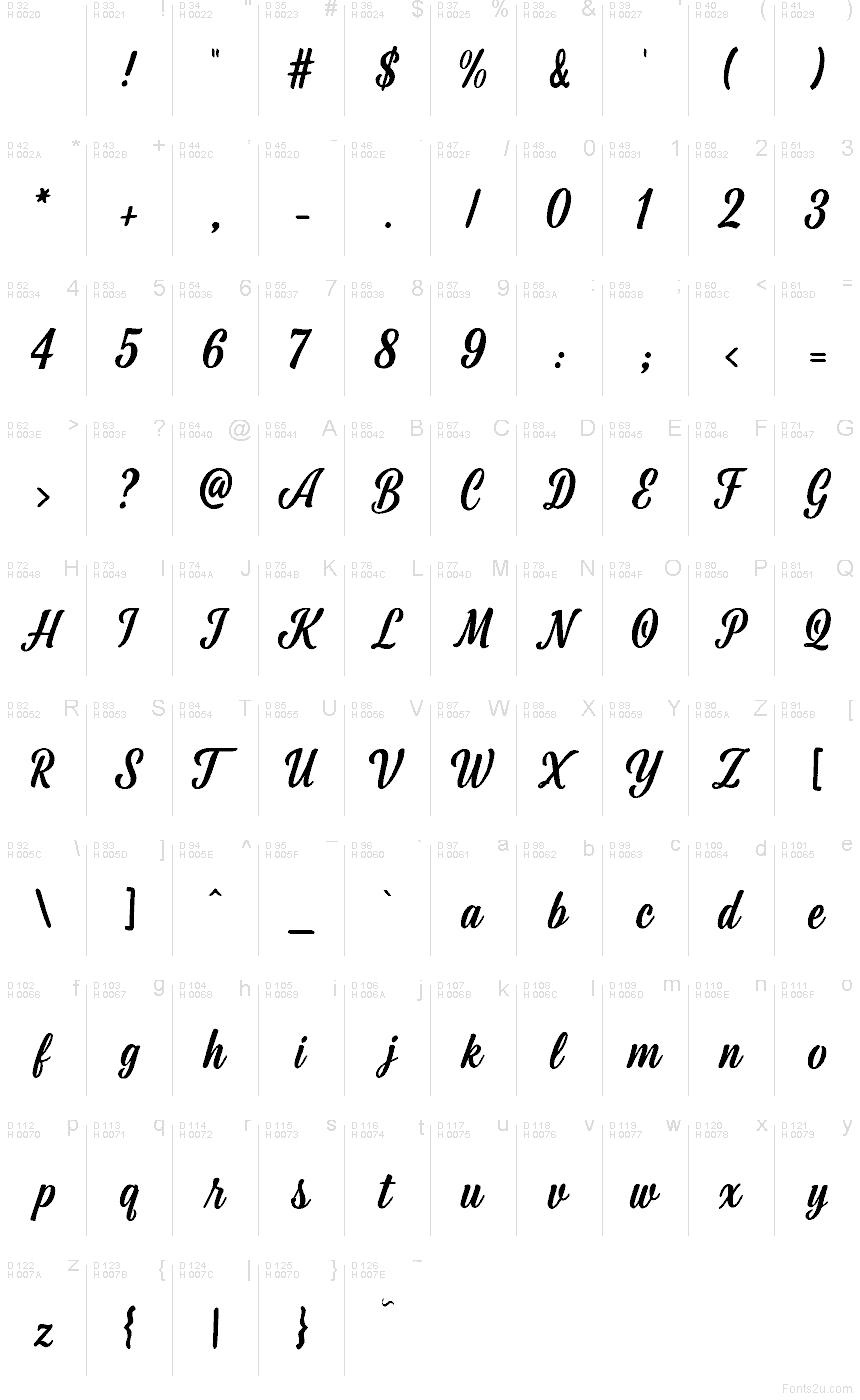
La Brioche Artisanale od BlackFridayFont je bezplatné písmo typu brush script s atmosférou francouzské pekárny, kreslené širokými, smyčkovými tahy a měkkými, ručně malovanými křivkami. Písmena mají štědré náběhy a zaoblené tvary, což dává písmu lehký a výrazný rytmus, který připomíná spíše výlohu obchodu než formální kaligrafii.
Přirozeně zapadne do brandingu kaváren, obalů cukrovinek, jídelních lístků, etiket gurmánských potravin i promo titulků na sociálních sítích, kde potřebujete bezplatné písmo s vřelým, ručně psaným nádechem. Použijte ho pro krátké nadpisy, obálky nebo logotypy, protože dlouhé počáteční a propojovací tahy dodávají i několika málo písmenům plnou a hotovou podobu.